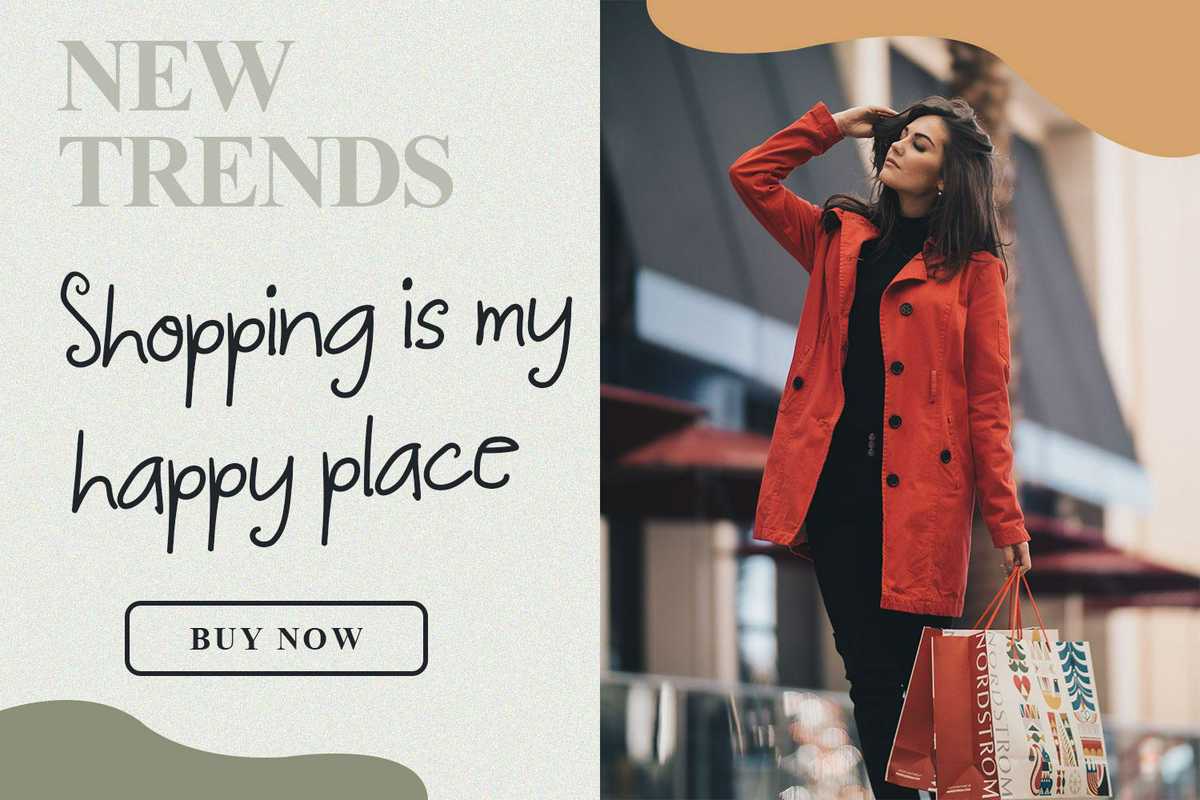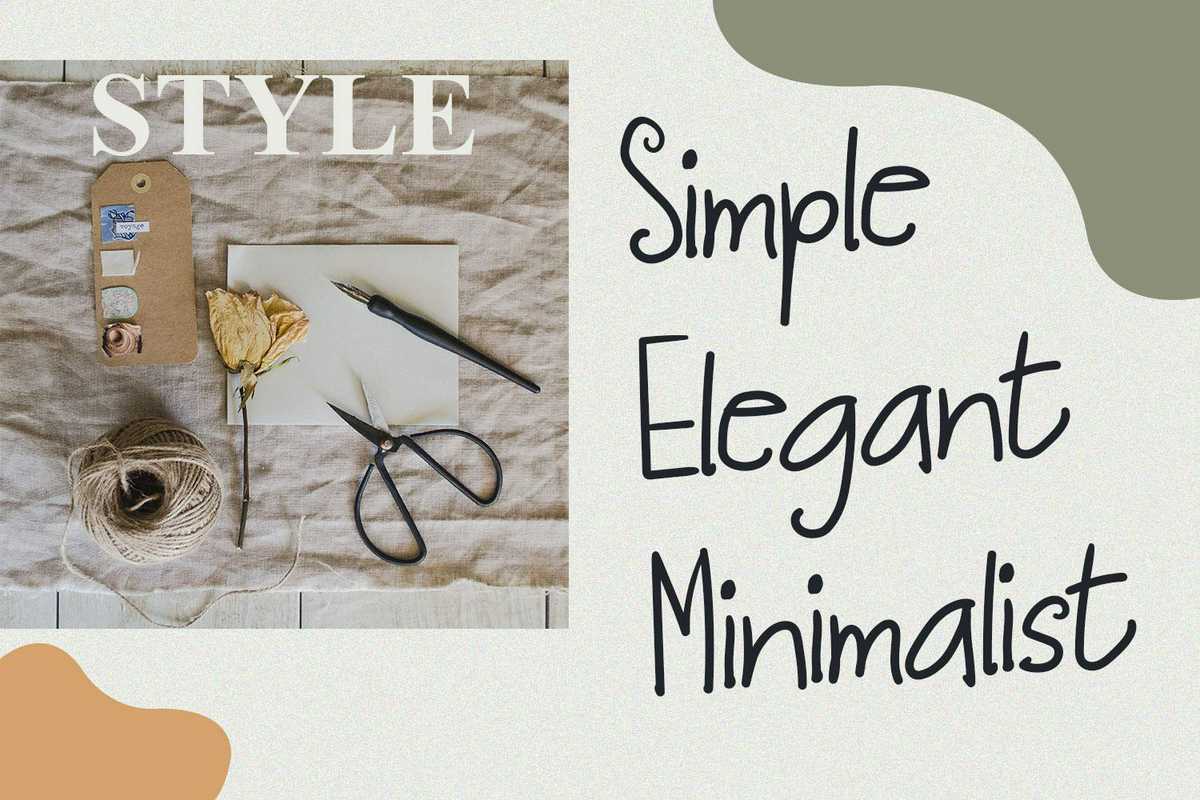
KalleiyOfont是一款具有移动和优雅功能的切割和绘制字体。此字体适用于各种矢量设计、打印,如数字婚礼、博客、在线商店、社交媒体,而打印可用于产品服装、配件、包、别针、徽标、名片、,水线和许多其他产品。Kalleiyofont是一种切割和绘制的、带有移动和优雅的显示字体。此字体适用于各种矢量设计、打印,如数字婚礼、博客、在线商店、社交媒体,而打印可用于现场的产品服装、配件、包、别针、徽标、名片、水线和许多其他产品。